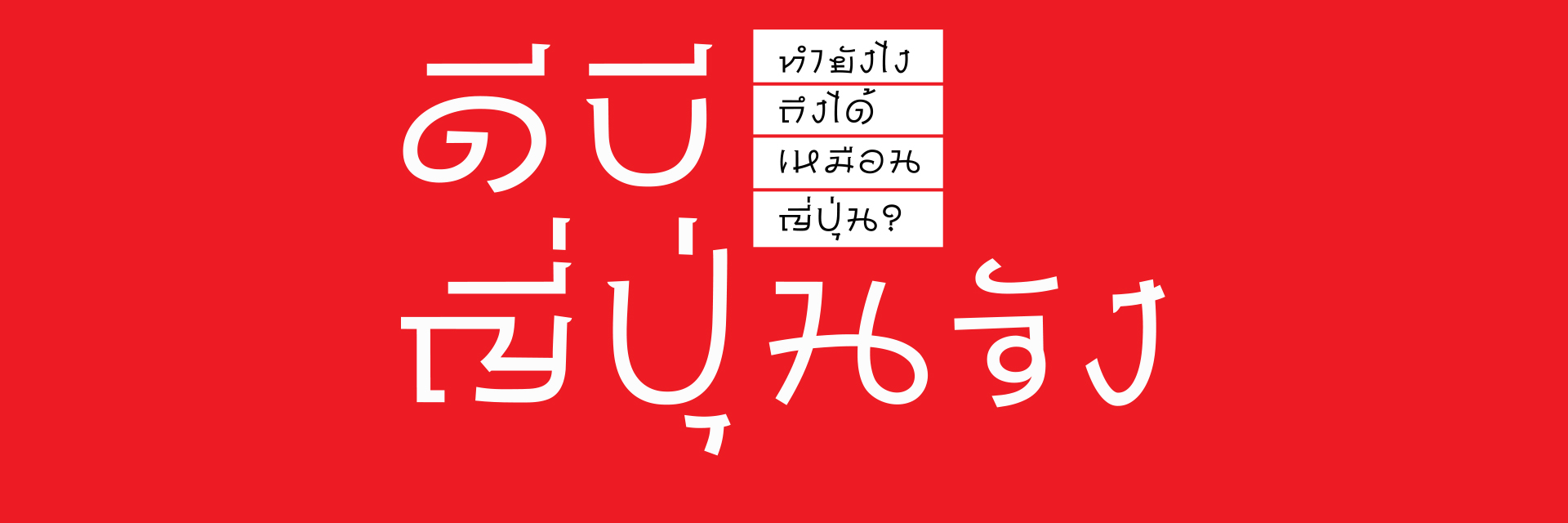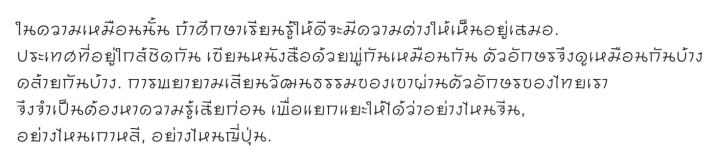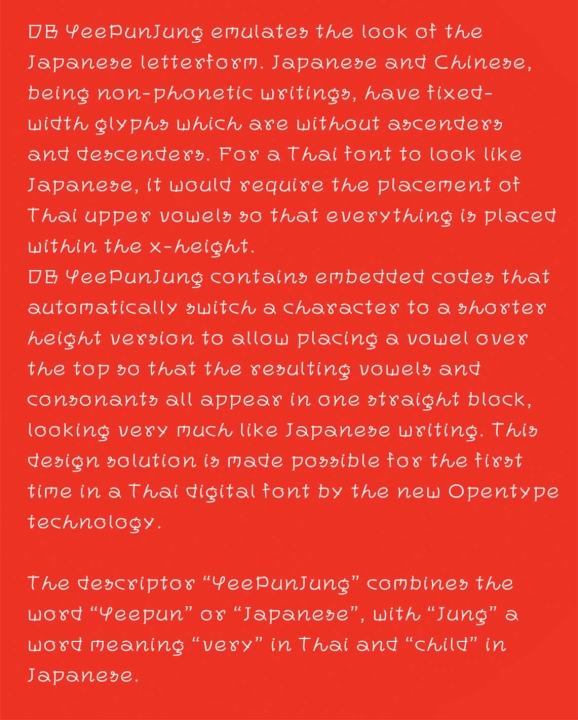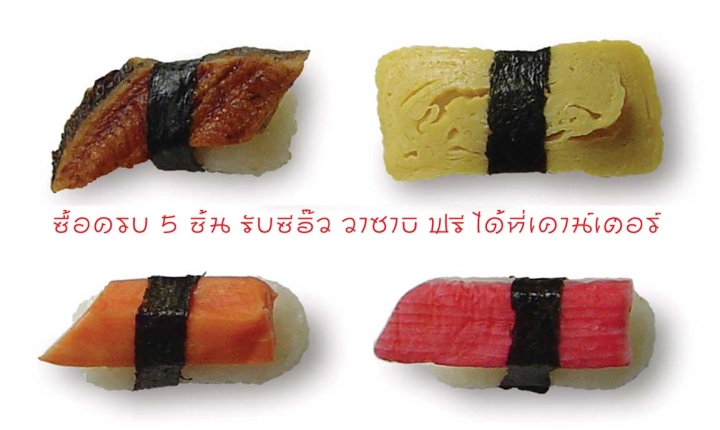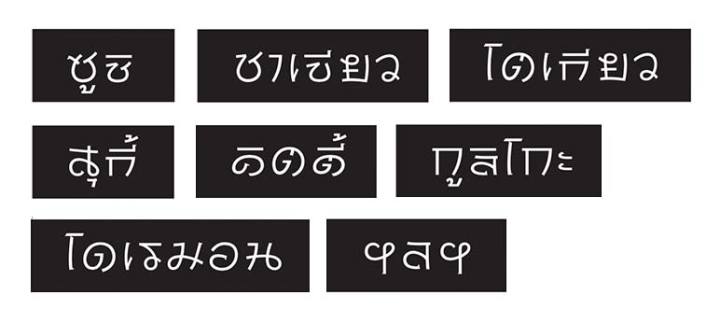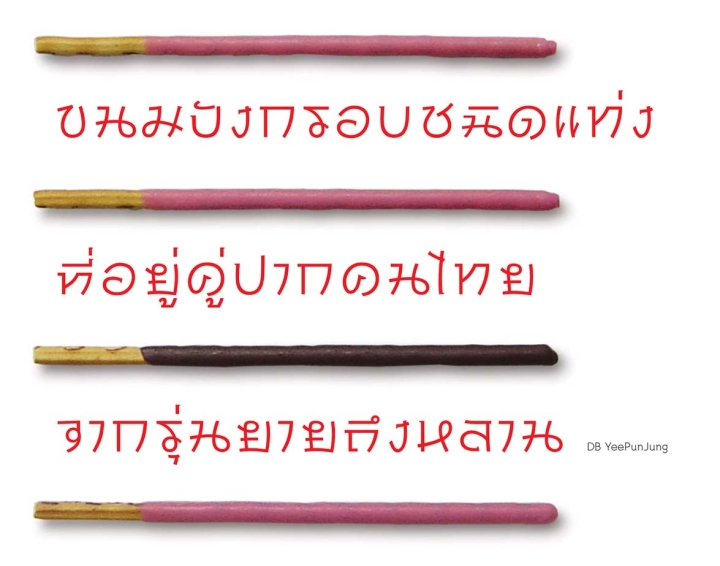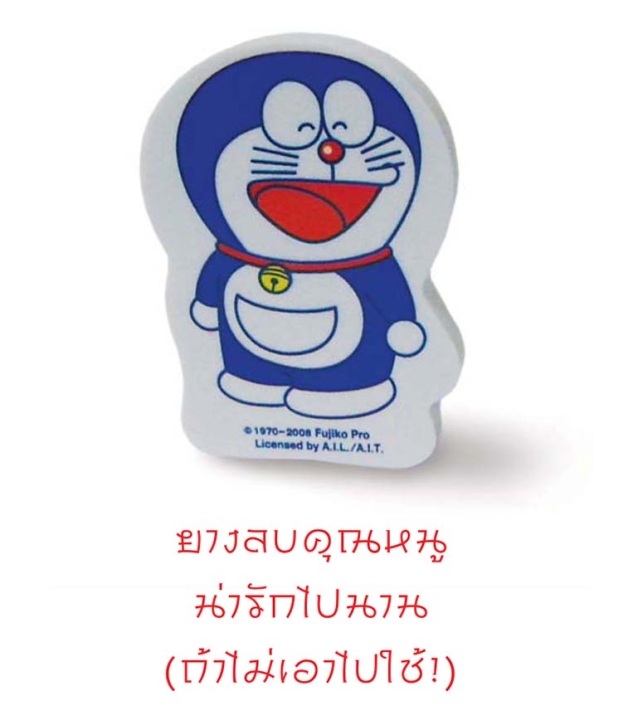
ต้องยอมรับว่า นอกจากวัฒนธรรมจีน, ตะวันตก ที่มีอิทธิพลต่อคนไทยมาช้านานแล้ว วัฒนธรรมญี่ปุ่นก็ซึมเข้ามาไม่น้อย ทั้งอาหารการกิน, การ์ตูน, แฟชั่น ฯลฯ แต่กลับไม่มีฟอนต์ความยืดหยุ่นสูงคล้ายลักษณะนิสัยของคนไทย สามารถประดิษฐ์ เลียนแบบตัวอักษรชาติอื่นๆ ได้ง่าย เช่น อักษรโรมันของชาว ตะวันตก, อักษรจีน, อักษรอินเดีย ฯลฯ แต่ที่ถูกทําเป็นตัวพิมพ์ หรือฟอนต์จริงๆ มักจะเห็นอยู่แค่แบบที่เลียนตัวอักษรโรมัน (ตัว display ส่วนใหญ่ของไทยอยู่ในกลุ่มนี้) และแบบที่เลียนตัวอักษรจีน (ซึ่งมีไม่กี่ฟอนต์ให้ใช้) เท่านั้น.
เวลานักออกแบบ จะทํางานที่อยากได้สําเนียงญี่ปุ่น (หรือเกาหลี) จึงมักใช้ฟอนต์ US Chawlewhieng, PSL Yaowaraj, DB HuadChai ฯลฯ ล้วน เป็นอักษรไทยเสมือนจีน) เพราะเห็นว่าเป็นประเทศเพื่อนบ้าน ที่มีวัฒนธรรมคล้ายๆ กัน เขียนหนังสือด้วยพู่กันมาก่อนเหมือนกัน เลยเหมาว่าใช้ฟอนต์แบบจีนๆ แทนได้, ความจริงถ้าจะกล่าวให้ถูกต้องแล้วการใช้ฟอนต์ไทยเสมือนจีนเพื่อแทนสําเนียงญี่ปุ่นนั้น ต้องใช้คําว่า "พออนุโลมได้" ทั้งนี้เพราะในภาษาเขียนของญี่ปุ่นมีตัวอักษรถึง 3 ประเภทรวมอยู่ด้วยกัน. ประเภทแรกคือ ตัวคันจิ เป็นอักษรญี่ปุ่นที่เขียนแบบจีน ความหมายก็เหมือนจีน แต่ออกเสียงต่างกัน. ประเภทที่สอง คือ ตัวฮีรากานะ เป็นอักษร ที่ชาวญี่ปุ่นออกแบบขึ้นมาเพื่อแทนคําออกเสียงคําในภาษาญี่ปุ่นเอง มีลักษณะเส้นตวัดไปมาดูโปร่งๆ ไม่ซับซ้อนเหมือนตัวคันจิ และประเภทที่ 3 คือ ตัวคาตากานะ ที่ชาวญี่ปุ่นประดิษฐ์ขึ้นใหม่เพื่อเขียนทับศัพท์คําภาษาต่างประเทศโดยเฉพาะ ลักษณะเส้นจะดูตรงๆ ค่อนไปทางอักษรเกาหลี ไม่อ่อนไหวเหมือนตัว ฮีรากานะ
โดยสรุป การใช้ฟอนต์ไทยเสมือนจีนจึงพออนุโลมให้ ดูคล้ายๆ ตัวคันจิของญี่ปุ่นได้ แต่ก็เป็นได้แค่ความเป็นญี่ปุ่น ที่คนญี่ปุ่นหยิบยืมของจีนมา. ถ้าจะทําฟอนต์ไทยเสมือนญี่ปุ่นแล้ว ทางที่ดีควรยึดเอาตัวฮีรากานะเป็นหลักจะดูเป็นญี่ปุ่นมากกว่า เพราะไม่เหมือนทั้งจีน (แบบตัวคันจิ) และเกาหลี (แบบตัวคาตากานะ) นั่นเอง
ไหนๆ จะทําฟอนต์เลียนแบบอักษรญี่ปุ่นทั้งที ผมคิดว่า ชุดแรกที่ออกมาน่าจะดูต่างจากตัวไทยเสมือนจีน (รวมทั้งตัวอักษรไทยประดิษฐ์เลียนแบบจีนที่ทําใช้เฉพาะกิจไม่กี่ตัว) ที่มักจะเน้นลักษณะเส้นพู่กันจีนเป็นสําคัญ. ผมจึงเลือกสไตล์ตัวฮีรากานะที่เป็นเส้นน้ําหนักเสมอกัน แทนแบบเส้นที่มีความหนักเบา อย่างที่เกิดจากปลายพู่กัน เพราะนอกจากจะดูต่างจากตัวไทยเสมือนจีนเดิมๆ เท่าที่เคยมีมาแล้ว เส้นน้ําหนักแบบสม่ำเสมอ ยังให้ความรู้สึกที่ทันสมัยกว่า เนื่องจากมันหลุดพ้นความเป็นเส้นพู่กันซึ่งค่อนไปทางอนุรักษ์นิยม.
DB YeePunJung มีการเก็บรูปสระบนให้ต่ำลง เหมาะสำหรับการจัดวางตัวอักษรในแถบ
ปรกติแล้วฟอนต์ไทยมาตรฐานทุกชุดจะมีชุดอักษรโรมันสไตล์เดียวกันให้ใช้ร่วมด้วยเสมอ. ในตัวพิมพ์ชุดนี้ที่ผมให้ชื่อว่า DB YeePun ก็เช่นกันต้องออกแบบขึ้นใหม่ทั้ง 2 ภาษาจึงสมบูรณ์ ทันทีที่ฟอนต์ DB YeePun ซึ่งได้อิทธิพลมาจากฮีรากานะเต็มๆ เสร็จเรียบร้อย เราพบว่าการออกแบบ "ฮีรากาไทย" นั้นง่ายกว่า "ฮีรากาโรมัน" เสียอีก เพราะตัวพยัญชนะไทยมีลีลาการเดินเส้นใกล้เคียงกับฮีรากานะมากกว่า อย่างไรก็ตามผลลัพธ์ที่ออกมาดู เหมือนยังมีจุดอ่อนที่ทําให้ดูแตกต่างจากฮีรากานะที่เป็นต้นแบบอยู่บ้างเล็กน้อย. กล่าวคือในขณะที่ฮิรากานะแท้ๆ แต่ละตัวจะถูกจํากัดพื้นที่อยู่ในกรอบสี่เหลี่ยมขนาดความสูงเท่าๆ กันนั้น "ฮีรากาไทย" กลับมีสระบน (โดยเฉพาะพวกสระ อิ อี อึ อื ที่มีขนาดเส้นเด่นชัดกว่าวรรณยุกต์หรือสระล่าง) ที่ทําให้แนวเส้นบนของแถวอักษรดูกระโดกกระเดกขึ้นๆ ลงๆ ไม่เรียบร้อยเป็นระบบเหมือนฮีรากานะ, เช่นเดียวกับเส้นหางที่ขึ้นๆ ลงๆ ในตัวพิมพ์เล็ก (small letter) ของตัว "ฮีรากาโรมัน".
ถ้าจะยึดการอ่านง่ายเป็นหลักแล้ว ลักษณะที่เป็นปัญหาดังกล่าวของ DB YeePun ถือว่าควรอนุโลมปล่อยไป. แต่ถ้าอยากให้มันดูเป็นฮีรากานะมากกว่านี้ ผมคิดว่าน่าจะจัดการกับตัวพยัญชนะที่มีสระบนกํากับทั้งหมดให้มันเตี้ยลง เพื่อเปิดพื้นที่ให้สามารถเลื่อนแนวเส้นนอนสระบน (โดยเฉพาะสระ อิ อี อึ อื) ให้ลงมาเสมอแนวความสูงของตัวพยัญชนะปรกติ (ส่วนพวก วรรณยุกต์, การันต์, สระล่าง อนุโลมให้ล้ำเส้นแนวกรอบตัวพยัญชนะได้ เพราะขนาดค่อนข้างเล็ก), สิ่งที่ผมพูดนี้ในอดีตจะทําได้ก็แต่เพียงการเขียนประดิษฐ์เป็นคําๆ ใช้เท่านั้น ไม่สามารถทําเป็นตัวพิมพ์ได้ แต่วันนี้เทคโนโลยีในการสร้างตัวพิมพ์ของโลกเราเปลี่ยนแปลงไปมากแล้ว จึงแทบไม่มีอะไรที่เราทําไม่ได้ นอกจากไม่เริ่มคิดที่จะทํา, FontLab ซึ่งเป็นซอฟแวร์ที่ใช้สร้างฟอนต์โดยเฉพาะนั้นจะมีสมรรถนะ (feature) พิเศษอยู่อันหนึ่ง ที่เรียกว่าลิเกเจอร์ (ligature), เพียงแต่เราออกแบบพยัญชนะ ก-ฮ ให้มี 2 ชุด คือพวกตัวสูงปรกติและพวกตัวเตี้ยลงเล็กน้อย (เพื่อหลบที่ให้สระบน) และออกแบบสระบนทั้งหมดโดยจัดวางให้ตําแหน่งเส้นแนวนอนของมัน อยู่เสมอกับระดับความสูงของพยัญชนะตัวปรกติ. กรณีที่พิมพ์สระบนตามหลังตัวพยัญชนะใดก็ตาม เราสามารถเขียนคําสั่งให้มันไปเลือกพยัญชนะพวกตัวเตี้ย (ในชุดที่ 2) มาใช้ร่วมกับสระบน (ที่ถูกลดระดับตําแหน่ง) แทนพยัญชนะตัวปรกติ (ในชุดที่ 1) ที่เพิ่งพิมพ์ผ่านไปหยกๆ พอคุณกดคีย์บอร์ดพิมพ์สระบนปุ๊บ ตัวพยัญชนะเป็นเตี้ยปั๊บ ราวกับคุณมีนิ้ววิเศษ, DB YeePun เดิมเมื่อผ่านกระบวนการออกแบบใหม่นี้จึงดูเหมือนภาษาญี่ปุ่นมากขึ้น เลยให้ชื่อใหม่ว่า DB YeePunjung. คําว่า "จัง" ของไทยแปลว่า "มาก" ส่วนญี่ปุ่นแปลว่า "เด็ก" จึงเหมาะจะใช้เป็นชื่อเพื่อแสดงความน่ารัก ร่วมสมัยแบบ ญี่ปุ่น-ญี่ปุ่น นั่นเอง
DB YeePun
ส่วนตัวพิมพ์เล็กใน ฮีรากาโรมัน ที่อยู่ใน DBYeePunJung นั้นช่างหัวมัน (ความจริงต้องช่างหางมันถึงจะถูก) คงปล่อยไว้ อย่างเดิมเหมือนใน DB YeePun.
DB YeePun นั้นจะใช้เป็นตัวพาดหัว, ตัวหัวข้อรอง, ตัวโปรย หรือตัวเนื้อความสั้นๆ (ที่ขนาดปอยต์ไม่เล็กจนเกินไป) ก็ได้ แต่ถ้าอยากได้สําเนียงญี่ปุ่นแบบจังๆ เป็นคํา, วลี หรือ ประโยคไม่ยาวมากในการพาดหัว ให้เลือก DB YeePunjung (ใช้ได้กับโปรแกรมที่รองรับ ligature เท่านั้น เช่น IndesignCs, IllustratorCS) จะดูมีรสนิยมกว่า